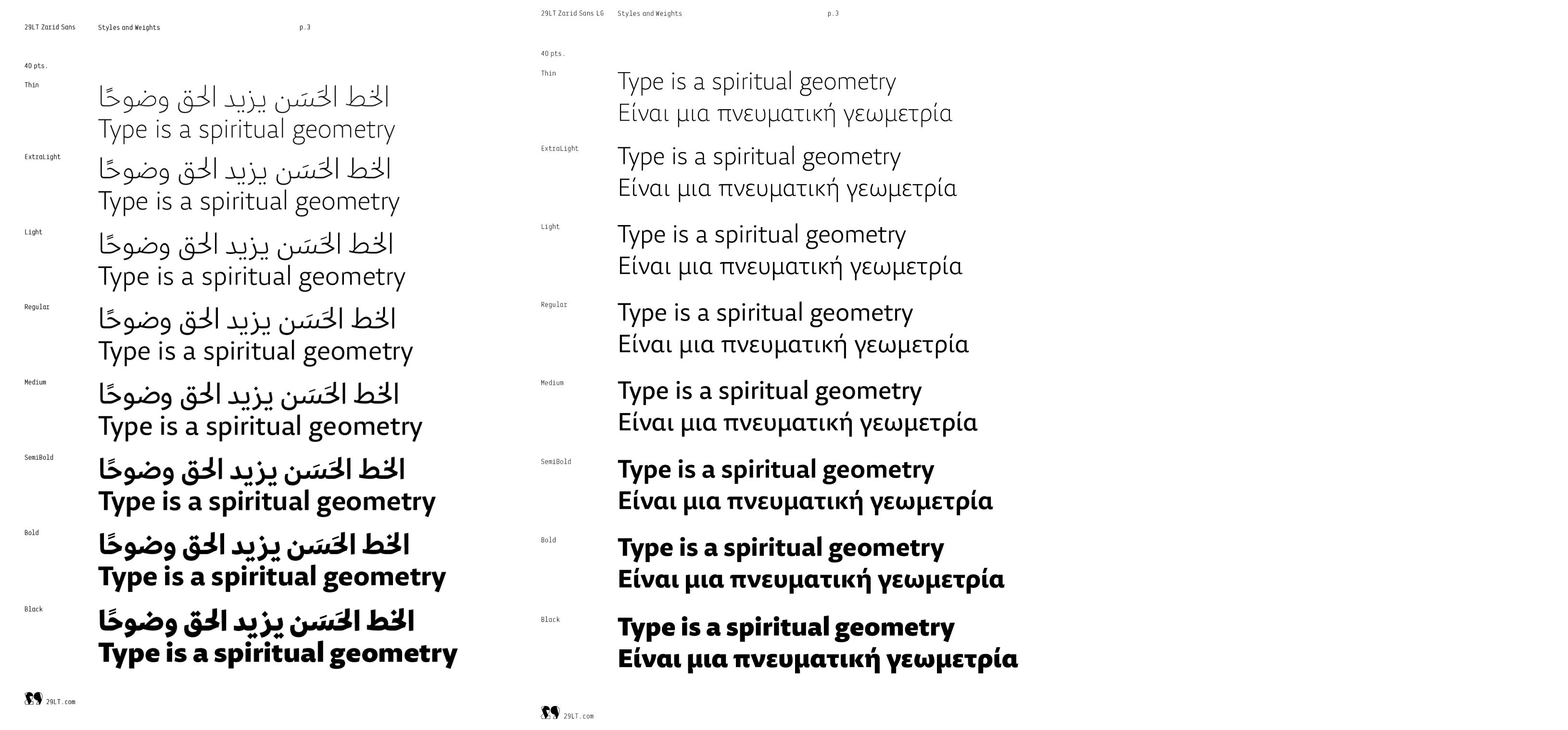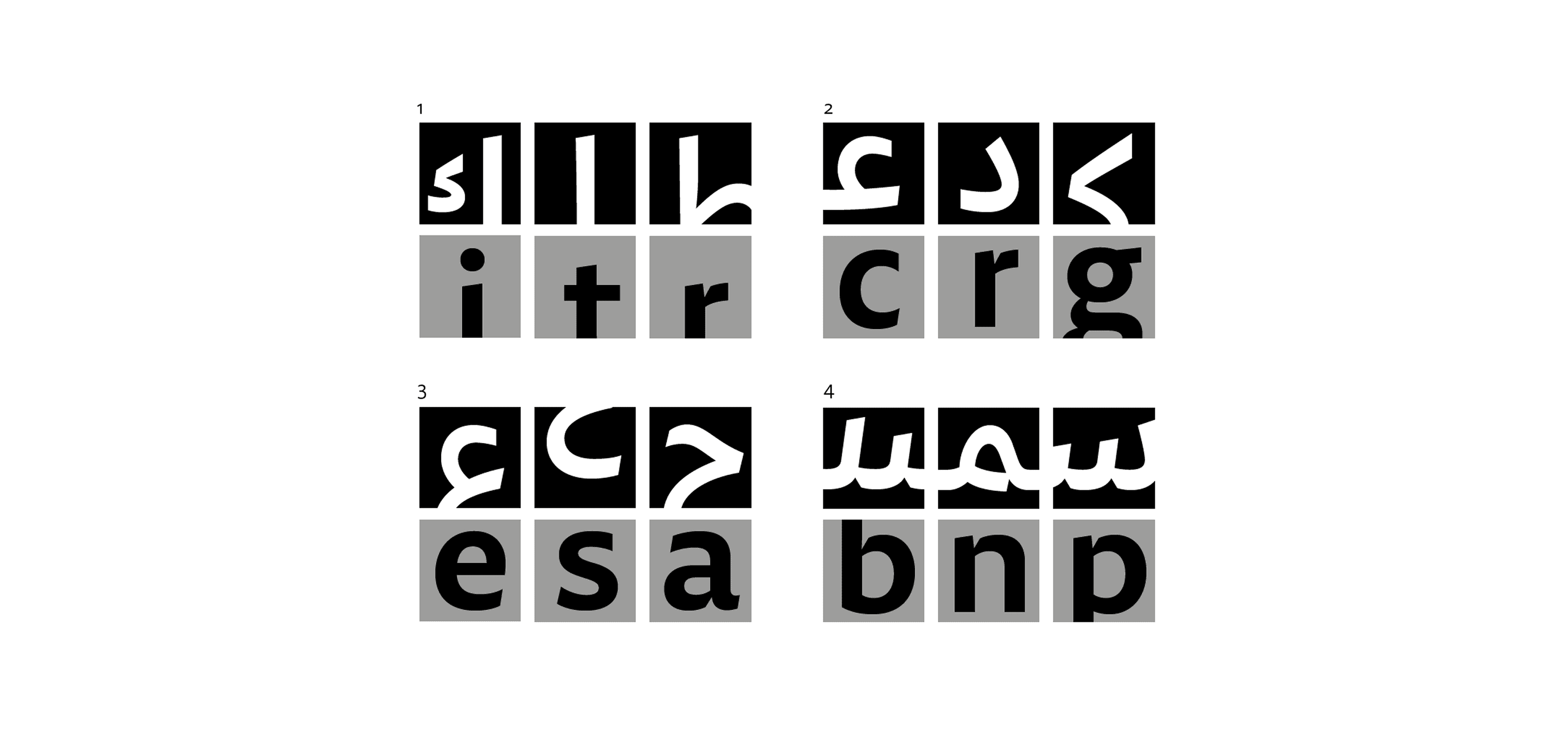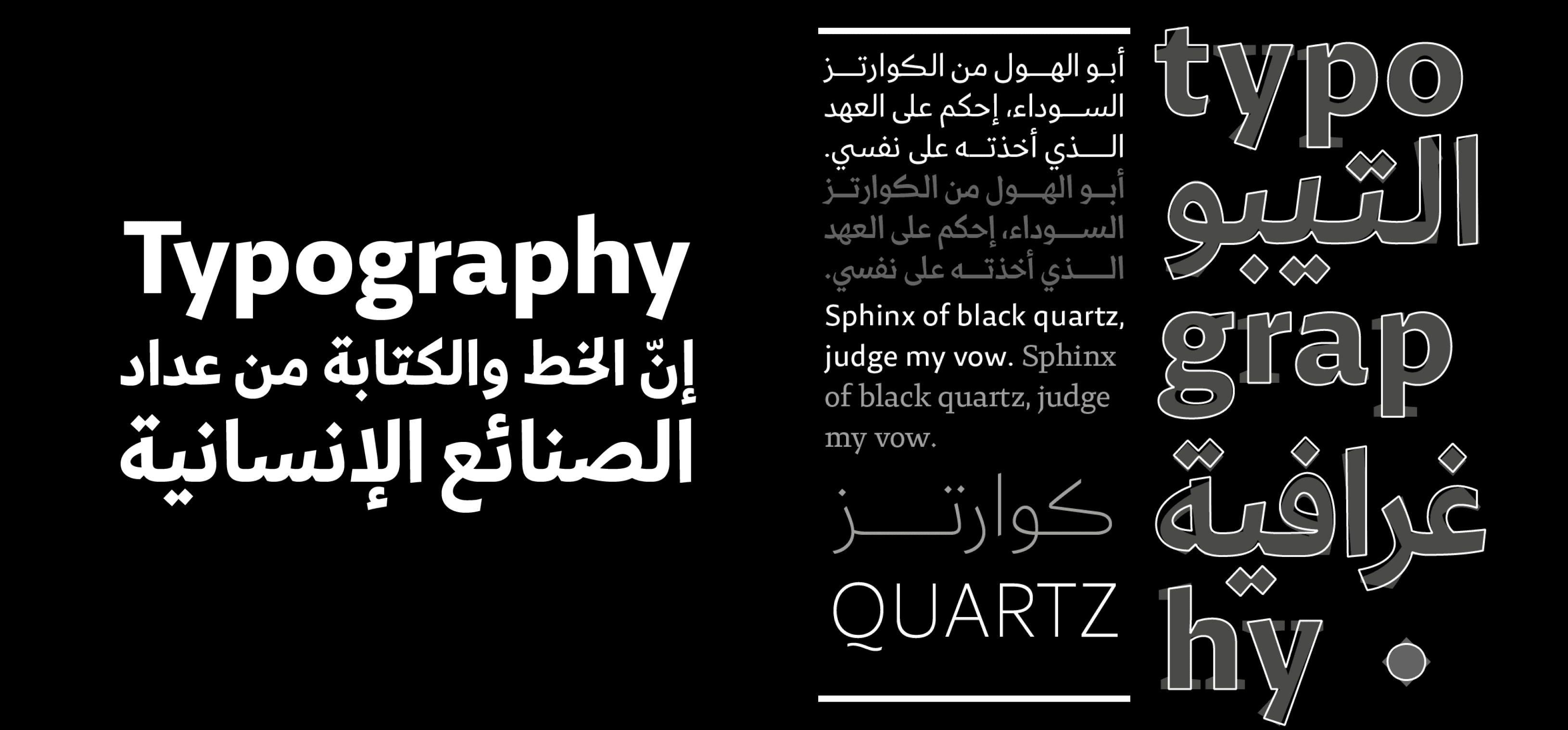
يتميّز خط زرد سنس بتصميم عصري يجمع بين البساطة والوضوح في الحروف، مما يجعله مثاليًا للاستخدام في النصوص التحريرية، واجهات المستخدم، والعلامات التجارية. يتوفر بمجموعة واسعة من الأوزان (من الرقيق جدًا إلى العريض جدًا)، مما يمنح المصممين مرونة كبيرة في تطبيقه على مختلف أنواع المشاريع.